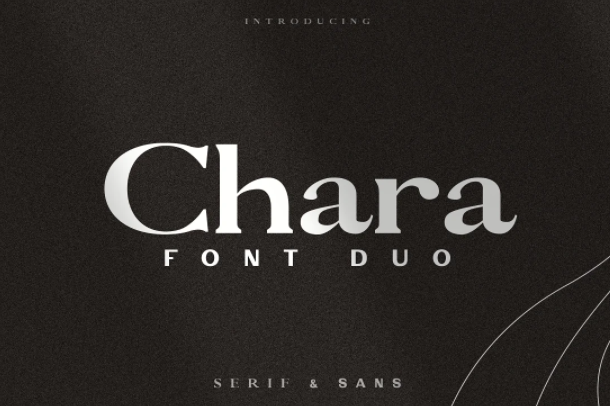
Представляем Chara - элегантный элитный шрифтовой дуэт современного sans-serif и классического serif шрифтов.
Шрифтовая комбинация помогает создавать элегантные дизайны и работает в крупных заголовках, логотипах и небольших абзацах. Идеально подходит для всех видов брендинговых проектов и маркетинговых целей. Вы можете комбинировать их бесконечными способами и создавать уникальные блокировки. Более того, вы также получите 9 бонусных бесплатных макетов логотипов, созданных с помощью Chara, которые вы сможете настроить в Adobe Illustrator.